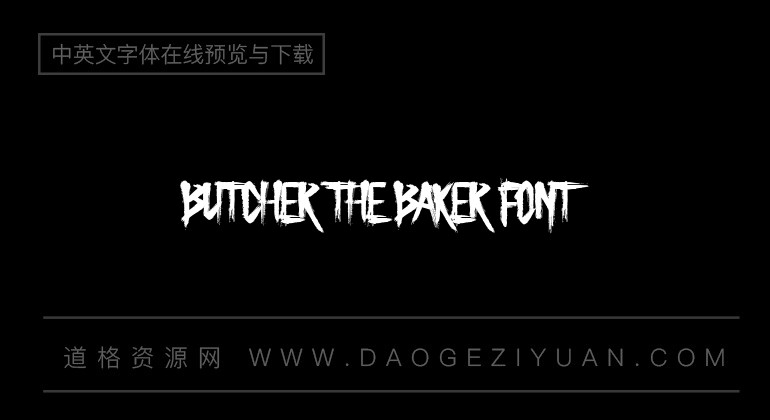
Butcher the Baker Font 是一种粗糙的手写字体,适用于多种设计领域,如海报、标志、横幅、包装等。它的字形具有明显的手写笔画特征,仿佛是由一个手艺精湛的面包师傅或屠夫用笔书写而成。 Butcher the Baker Font 字体采用了大号字形,字母之间的间距较宽松,使得文字在阅读时更加清晰易懂。它的字母形态有些扭曲和变形,也加强了字体的手写风格,使其更加独特、有个性。 此外,Butcher the Baker Font 字体还包括了多种字形变化和特殊符号,以满足不同设计需要。总之,Butcher the Baker Font 字体是一款独特、有趣的字体,可以为设计师们的作品增添趣味和风格。内容介绍
Butcher the Baker Font是一款非常不错的手写艺术字体,具有很好的视觉感,适合于文化类的宣传设计、商业类品牌的广告和产品包装设计以及个性化文字排版等较多场景。